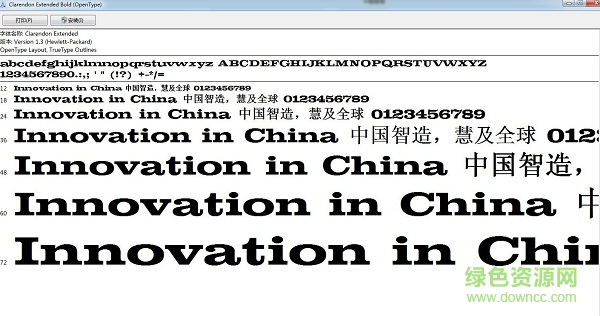
clarendon extended bold粗體
clarendon extended 字體是一款漂亮的粗體字體,字體造型規(guī)整,結(jié)構(gòu)嚴(yán)謹(jǐn),富有韻律感,常常用在正文大標(biāo)題或是海報(bào)設(shè)計(jì)方面,有需要者歡迎免費(fèi)下載!